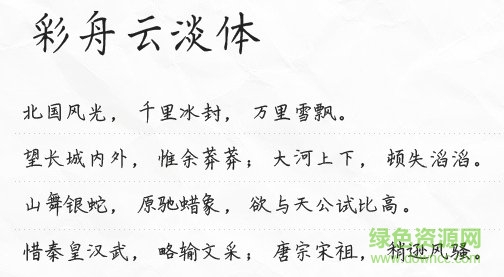
彩舟云淡字體是一款出自于思雨字庫(kù)的硬筆手寫(xiě)字體,同本系列的字體風(fēng)格類(lèi)似,端正簡(jiǎn)潔,無(wú)多余的修飾,筆畫(huà)平穩(wěn)矯健,清雅淡然,如果你喜歡,就來(lái)綠色資源網(wǎng)嘗試吧!
“彩舟云淡,星河鷺起,畫(huà)圖難足”——彩舟云淡體。
本字體是在國(guó)家標(biāo)準(zhǔn)簡(jiǎn)體字庫(kù)GB2312所包含6763漢字的基礎(chǔ)上,又增加了近200常用字,已經(jīng)覆蓋了大陸99.75%的漢字使用頻率,足以滿(mǎn)足日常需求。
思雨字庫(kù)以硬筆手寫(xiě)體為主,包括思雨鷓鴣飛、思雨紅豆體、隨風(fēng)逐夢(mèng)體等,字體大多數(shù)采用楷體書(shū)法為模板,更顯干凈大方,可以廣泛使用在藝術(shù)設(shè)計(jì)、廣告策劃等場(chǎng)合。